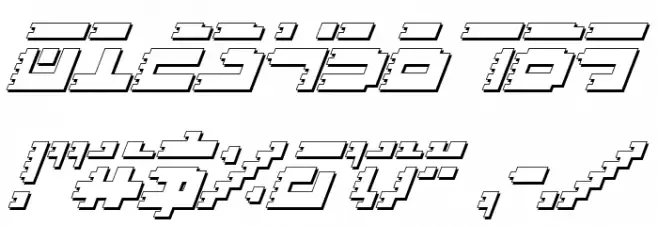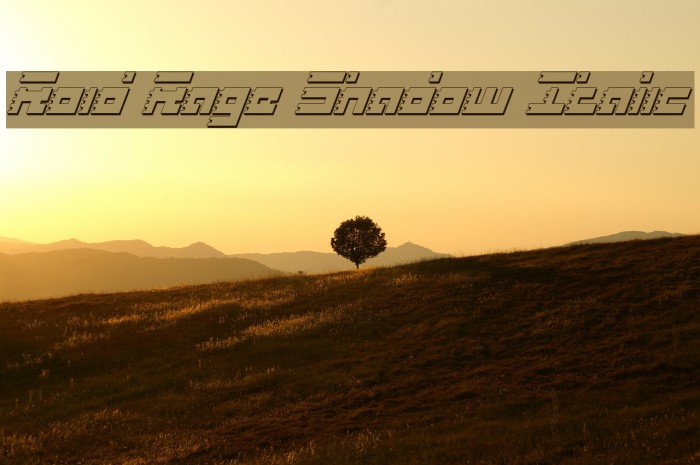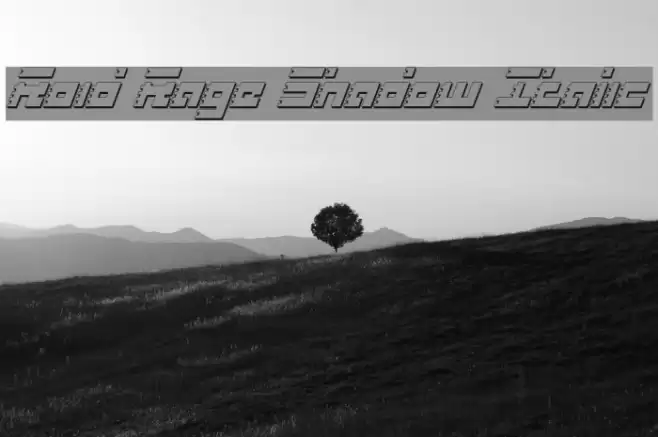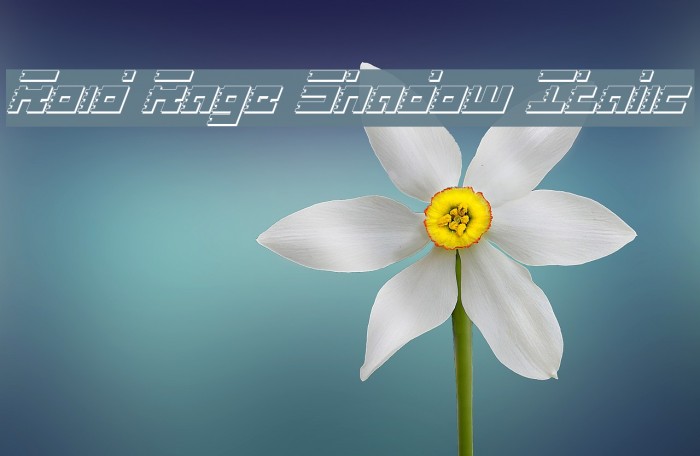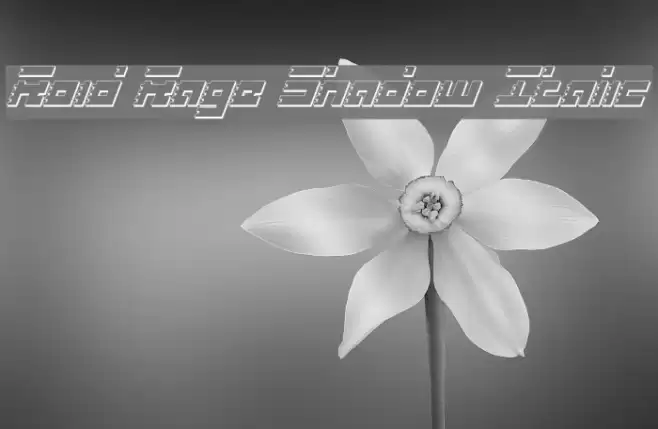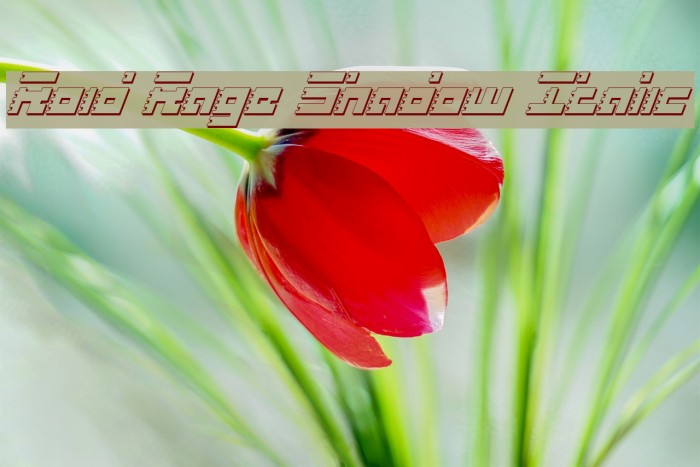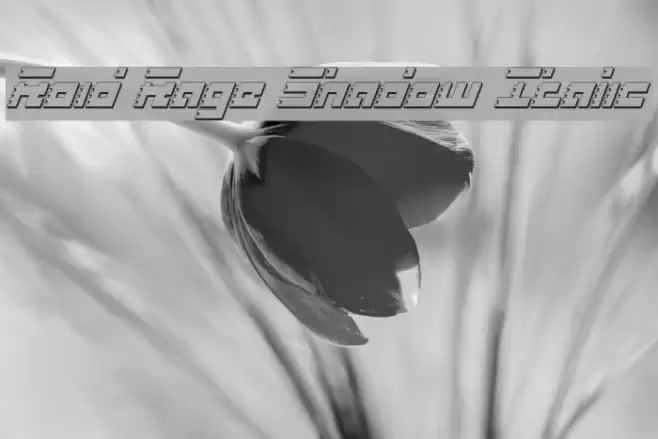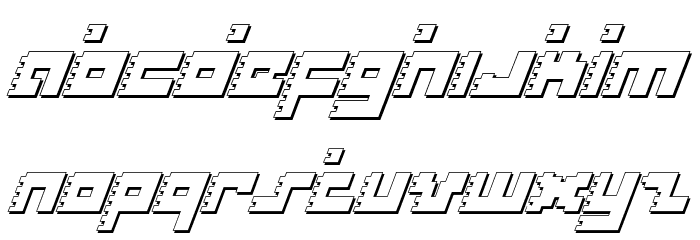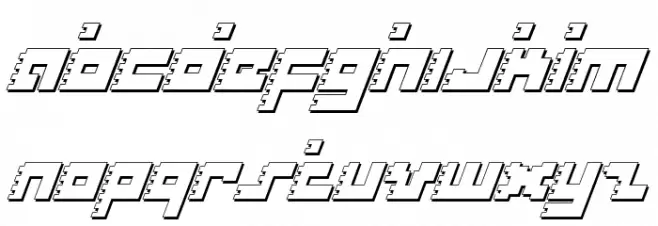
Roid Rage Shadow Italic Font
| 全体的なスタイル | Futuristic, Tech-inspired |
| おすすめプロジェクト | Ideal for video game titles, tech logos, futuristic posters, and digital media branding. |